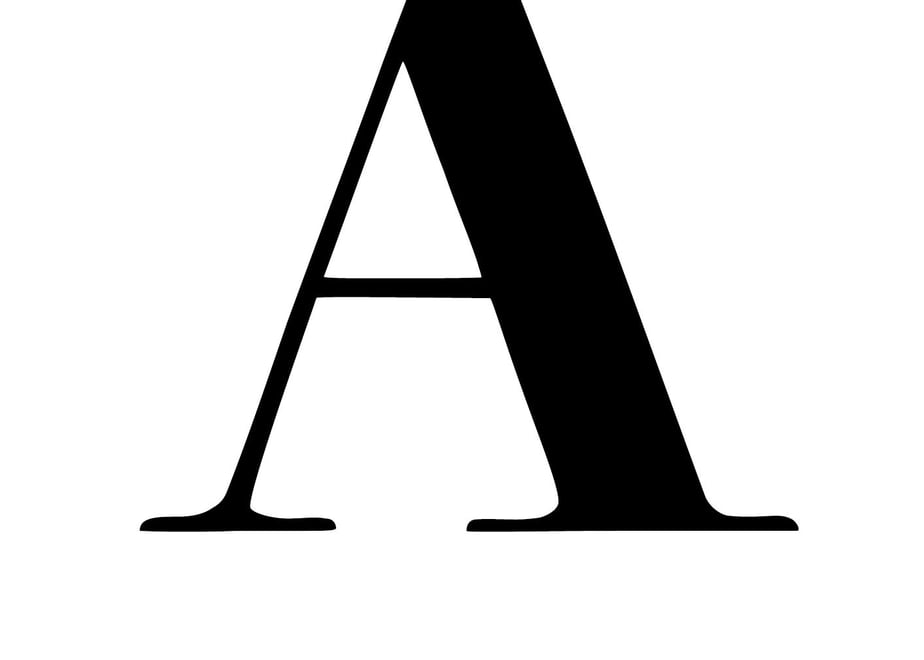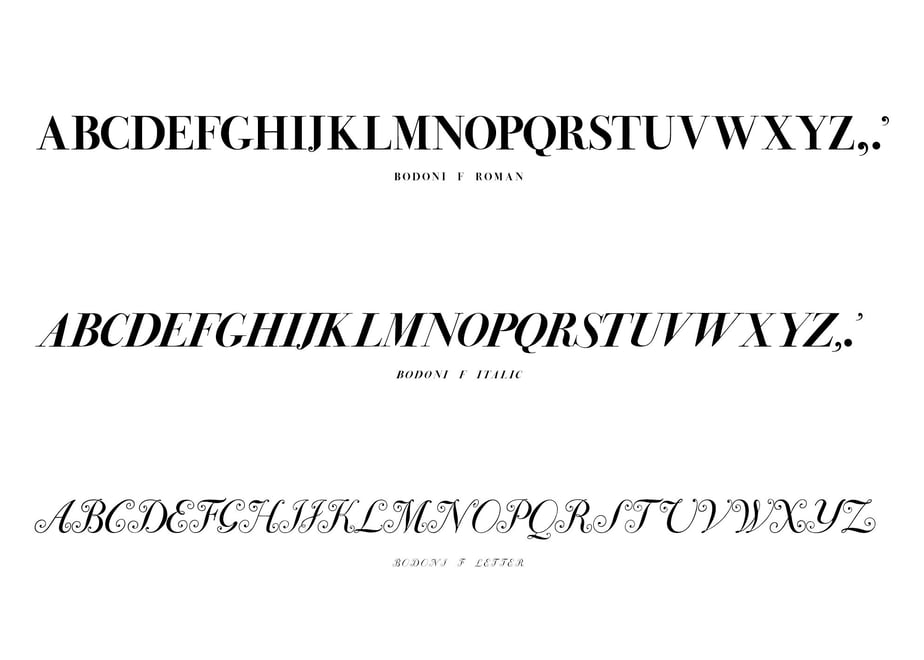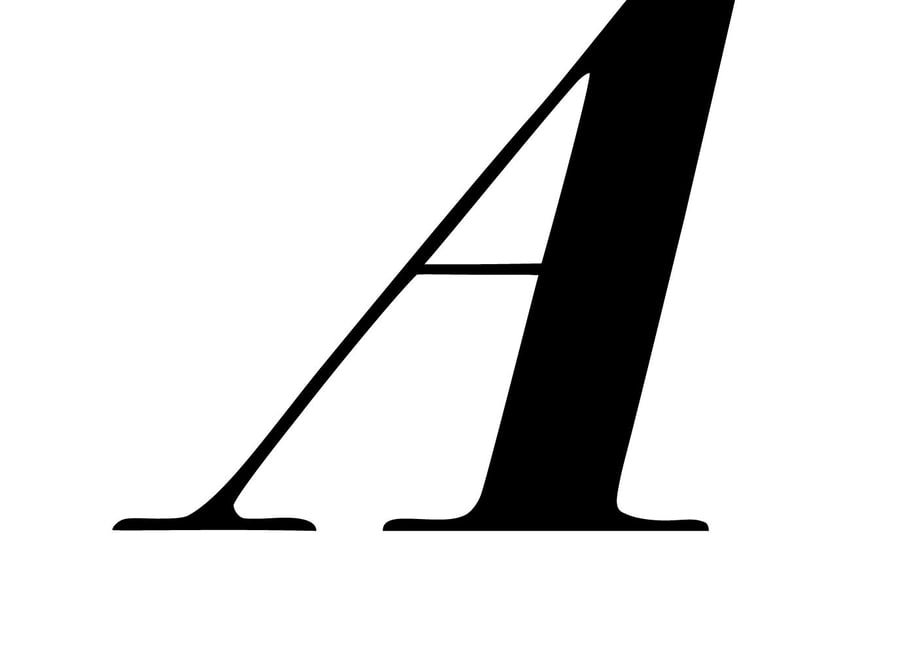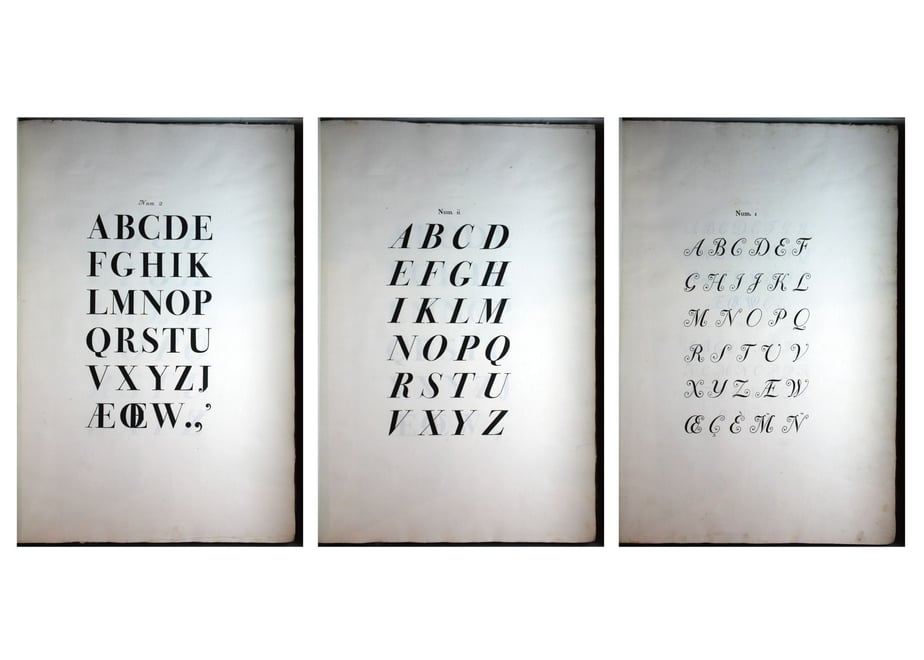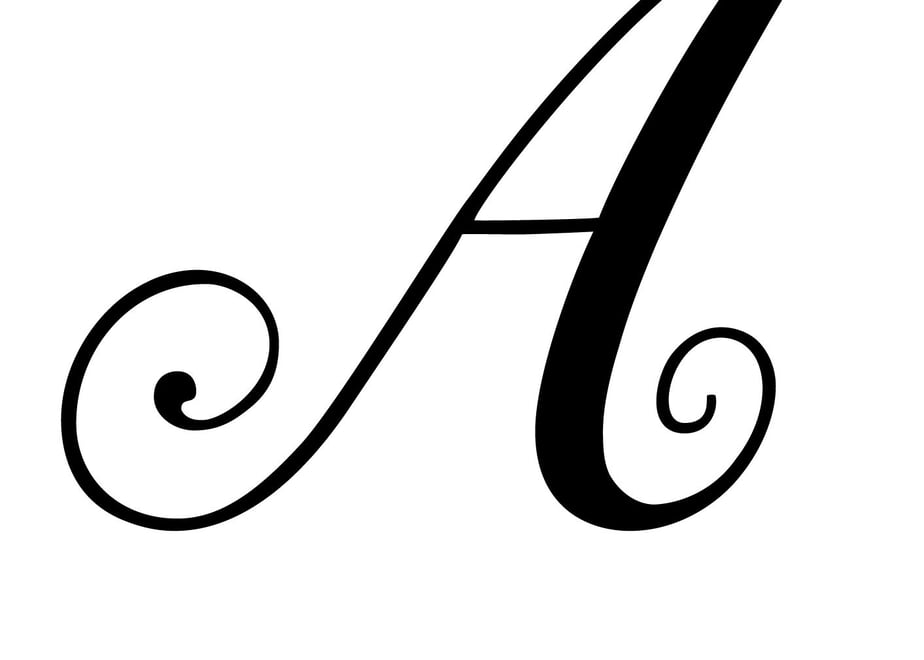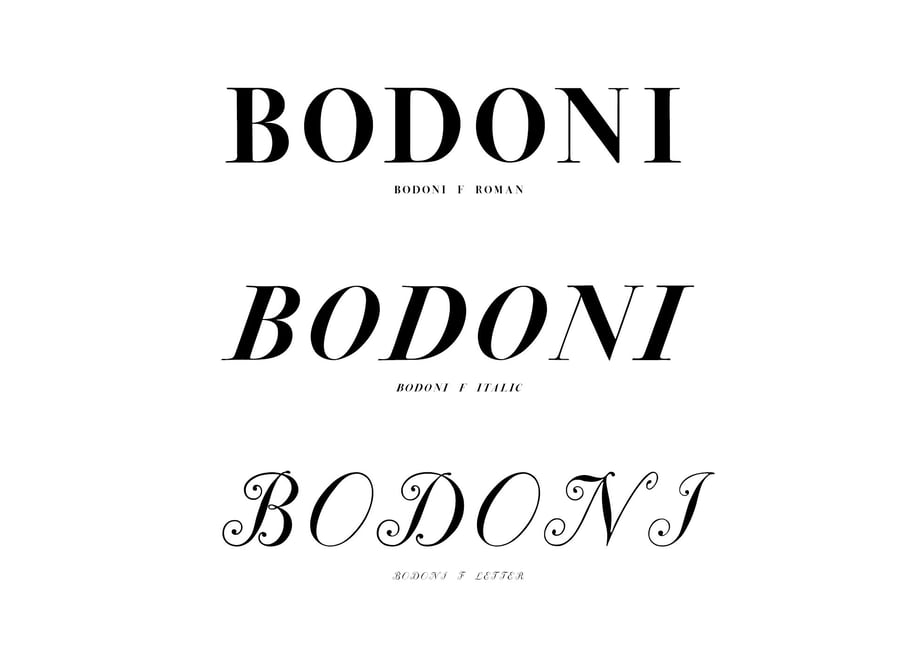
フォント:BODONI F
The English typeface "BODONI" has been recreated with the interpretation of fengfeel design.
○ Recorded characters
BODONI F ROMAN
"ABCDEFGHIJKLMNOPQRSTUVWXYZ ,.'"
BODONI F ITALIC
"ABCDEFGHIJKLMNOPQRSTUVWXYZ ,.'"
BODONI F LETTER
"ABCDEFGHIJKLMNOPQRSTUVWXYZ"
英書体「BODONI」をfengfeeldesign解釈で作り直しました。
○収録文字
BODONI F ROMAN
「ABCDEFGHIJKLMNOPQRSTUVWXYZ,.'」
BODONI F ITALIC
「ABCDEFGHIJKLMNOPQRSTUVWXYZ,.'」
BODONI F LETTER
「ABCDEFGHIJKLMNOPQRSTUVWXYZ」